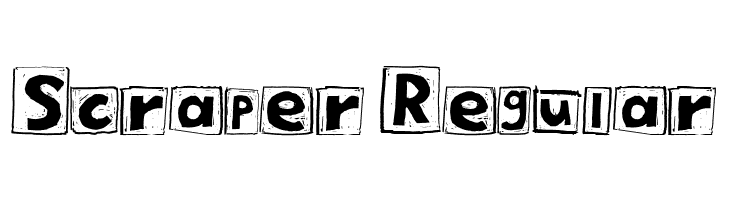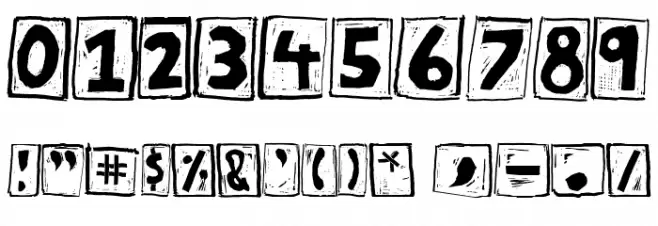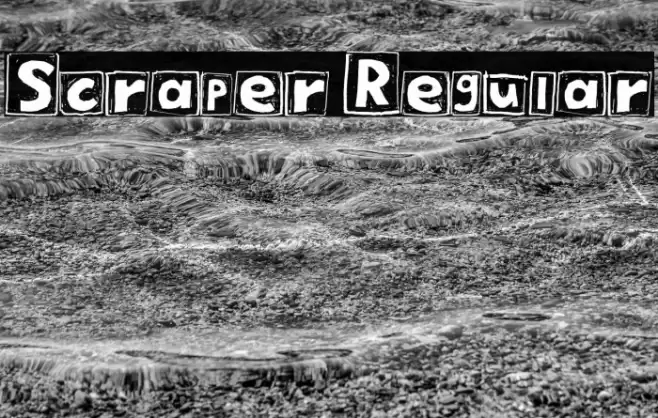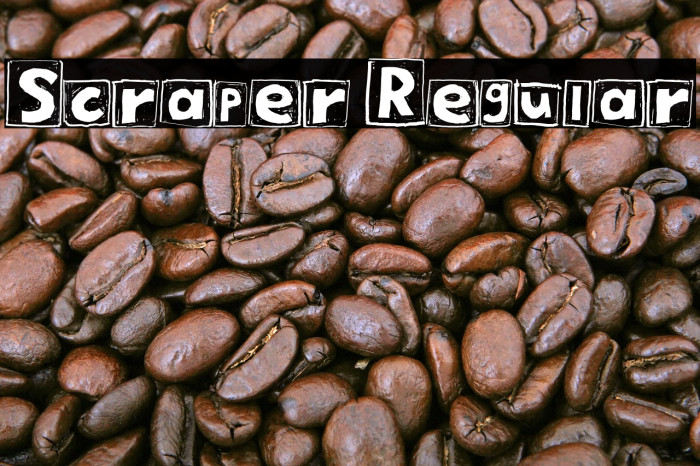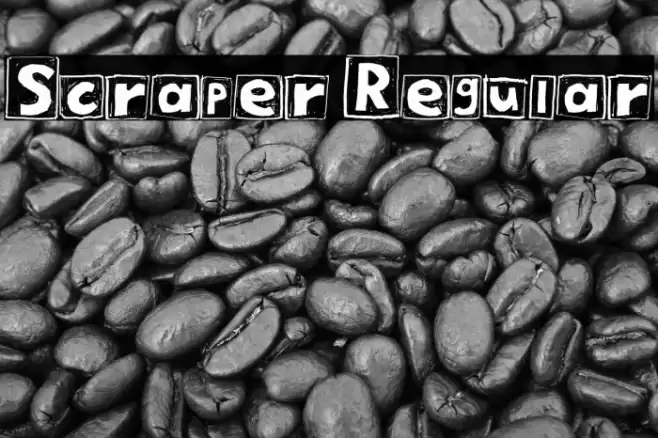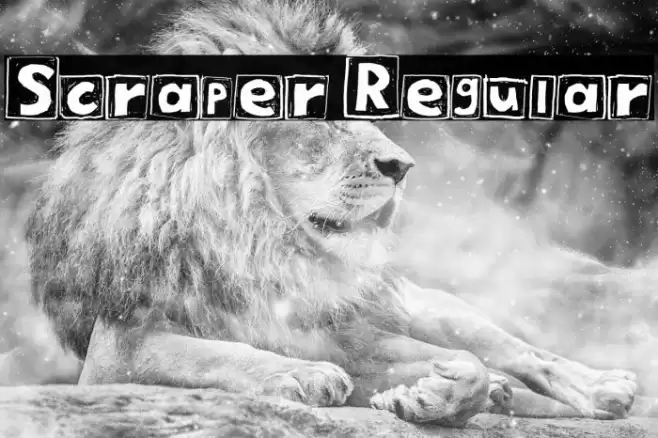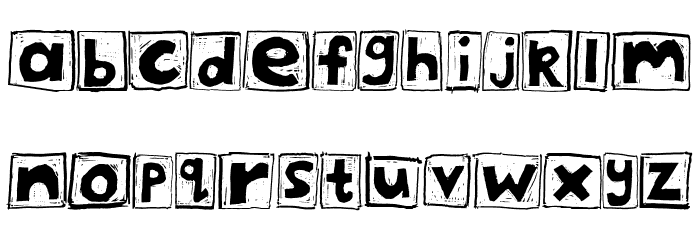
Scraper Regular Font
| Categorías | Decorative |
| Estilo general | Artistic, Playful, Handcrafted |
| Proyectos propuestos | Ideal for creative projects such as posters, album covers, children's books, and artistic branding materials. |